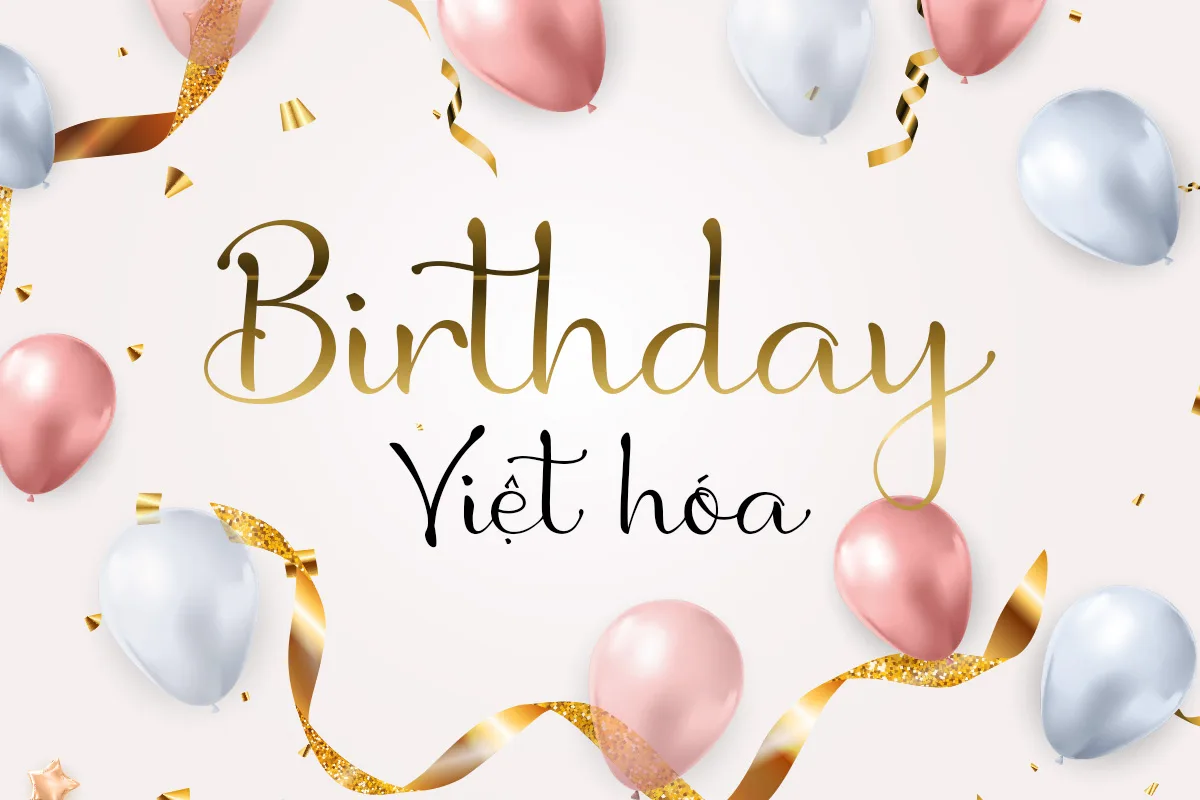
Birthday Việt hóa – Font chữ viết tay dịu dàng cho những khoảnh khắc yêu thương
Birthday Việt hóa là một kiểu chữ viết tay đầy cảm xúc, mang hơi thở của những lời chúc nhẹ nhàng và những kỷ niệm ngọt ngào. Với nét chữ mềm mại, độ cao chữ uốn lượn duyên dáng và sự cách điệu ở các đầu nét, font tạo cảm giác gần gũi như được viết bằng tay thật.
Bản Việt hóa được thực hiện chỉn chu, giữ nguyên vẻ bay bổng vốn có của font gốc, đồng thời tối ưu các dấu tiếng Việt để đảm bảo tính thẩm mỹ trong mọi câu chữ. Birthday phù hợp cho các thiết kế như: thiệp chúc mừng, thiệp cưới, poster sự kiện, bìa sổ tay hoặc bất kỳ ấn phẩm nào muốn truyền tải sự nhẹ nhàng, tinh tế và nữ tính.